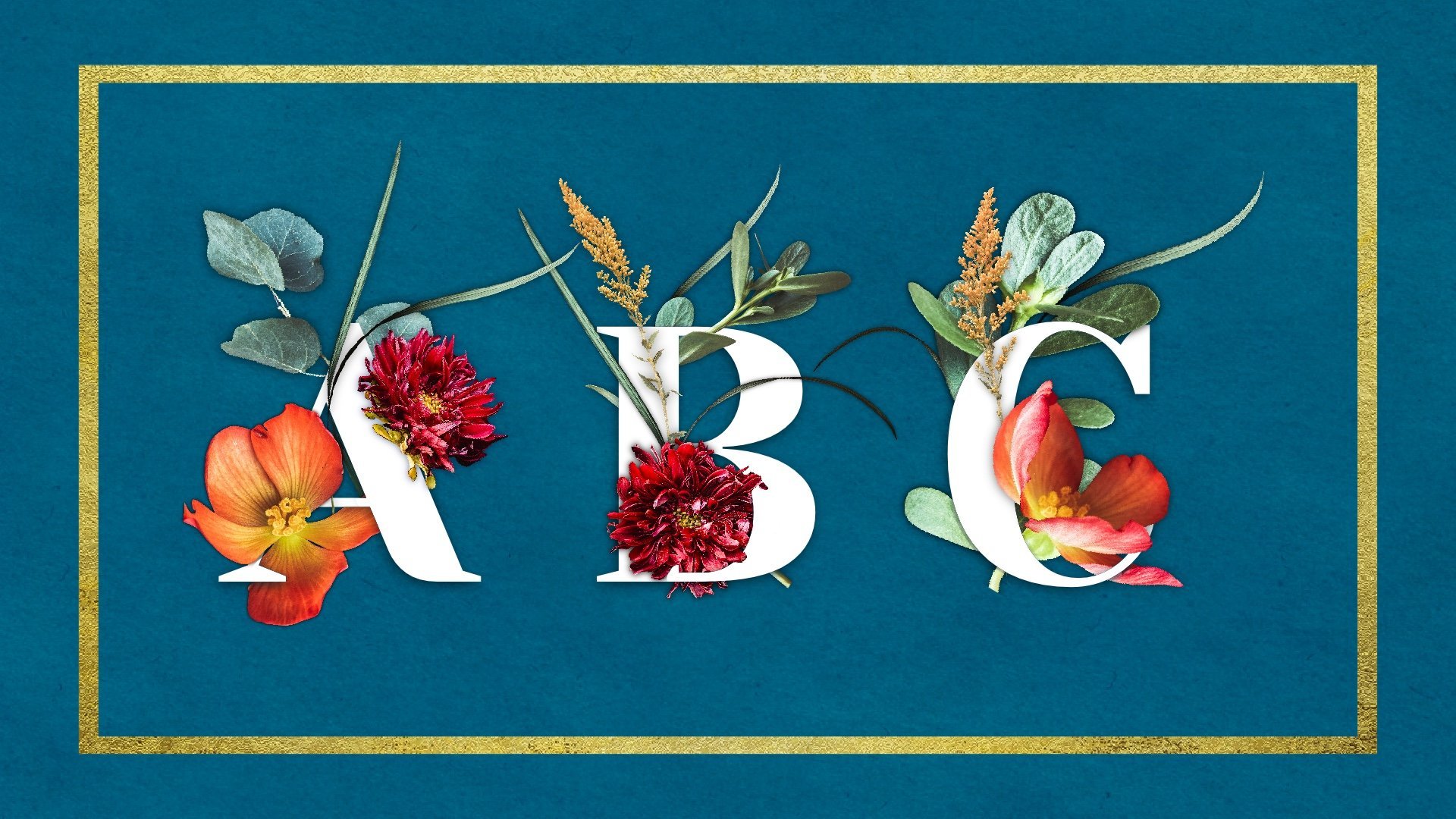
Masquage Procreate : créer une typographie époustouflante avec des fleurs entrelacées
Polices dans Procreate
Masques d'écrêtage dans Procreate
Masques de calques dans Procreate
Pratique plus de masque de couches
Entrelacer des fleurs avec une lettre
Floraux entrelacés avec un nombre
Bonus ! Astuces de masquage pour les réseaux sociaux
À propos de ce cours
Ce cours porte sur une seule chose : le masquage dans Procreate. À la fin de ce cours de 53 minutes, vous comprendrez les masques d'écrêtage et les masques de calques dans Procreate.
Pour le projet de cours, nous allons créer une belle typographie florale en utilisant du texte dans Procreate. Nous entrelacerons de magnifiques fleurs et feuilles numériques avec une seule lettre ou un seul numéro. Le projet est intentionnellement simple et vous pouvez donc vous focaliser sur les bases du masquage de calque.
Comme nous utilisons des fleurs et du texte numériques dans Procreate, des créatifs de tous niveaux pourront participer. Aucune compétence en dessin n'est nécessaire !
De cours, nous allons :
• Parcourir des polices gratuites dans Google Fonts
• Passer en revue brièvement Alpha Lock dans Procreate
• Explorer rapidement les masques d'écrêtage dans Procreate
• Entrelacer fleurs et feuilles avec une seule lettre en utilisant des masques de couches
• Entrelacer fleurs et feuilles avec un seul nombre en utilisant des masques de couches
1. Bande-annonce du cours: Bonjour, je suis Kelly Brand Burke. Je travaille en tant qu'artiste indépendant depuis 2013. J'adore créer de l'art numérique avec l'application Procreate. Et je vais vous raconter une petite histoire sur l'époque où j'ai commencé à créer de l'art numérique dans Procreate. C'était en 2015. Je n'arrêtais pas de voir ces magnifiques images entrelacées de mots, et je voulais vraiment apprendre à le faire. J'ai donc fait ce que je fais toujours. J'ai cherché mon intérieur sur Google, Google m'a dit que les masques à couches étaient la solution. J'ai trouvé des tutoriels YouTube sur le masquage dans Procreate géniaux, non ? Sauf que mon expérience n'a pas été géniale cette fois. J'adore apprendre grâce aux tutoriels YouTube. J'ai même créé des tutoriels Procreate sur YouTube. Mais pour ce sujet, enseignant passe à travers des masques à couches comme si c'était la chose la plus simple au monde. Je suis une artiste autodidacte, mais je n'arrivais pas à me concentrer sur les masques multicouches. Le découpage des masques était assez simple, mais les masques en couches, je n' arrivais pas à l'obtenir. Finalement, je l'ai découvert. Et puis, au bout d'un moment, j'ai oublié. Rincez et répétez l' ensemble du processus pendant des années. J'ai créé ce cours pour que vous puissiez comprendre le masquage dans Procreate. Ce cours se concentre sur une seule chose, le masquage dans Procreate. Pour le projet de classe, je vais vous expliquer comment s' entrelacent de magnifiques fleurs et feuilles à l'aide d'une seule lettre, puis d'un seul chiffre. À la fin de ce cours, vous comprendrez le masquage et comment entrelacer des images et des textes, puisque nous utilisons des fleurs numériques et des textes dans Procreate, les créatifs de tous niveaux seront capables pour participer. Aucune compétence en dessin n' est requise pour ce cours. J'utiliserai mon iPad, l'application Procreate de mon Apple Pencil, mais n'importe quel stylet compatible fera l'affaire. Mais attendez, il y a plus encore. Vous recevrez les meilleures fleurs et feuilles numériques. Je pourrais trouver une liste de polices gratuites suggérées et belles textures de fond prêtes à explorer le masquage dans Procreate. Allons-y. 2. Projet et ressources du cours: Le projet de classe consiste à entrelacer belles fleurs et feuilles avec une seule lettre, un seul chiffre ou les deux. Le projet de classe est volontairement simple afin que vous puissiez vous concentrer sur les bases du masquage des couches. Mais d'abord, nous allons parcourir les polices gratuites sur Google et choisir une police pour votre projet. Ensuite, nous explorerons la découpe de masques dans Procreate. C'est une leçon rapide. C'est à peu près cinq minutes. Nous allons passer le reste du cours sur les masques à couches. Je vais vous guider à travers chaque étape pendant que nous entremêlons des fleurs avec d'abord une lettre, puis un chiffre J'ai des atouts de classe pour vous aider, y compris une variété de textures de fond, une liste de polices gratuites suggérées et les meilleures fleurs numériques que j'ai trouvées chez Katherine d'Avalon Rose Designs. Elle nous fournit généreusement de magnifiques fleurs et feuilles. J'ai également créé un guide étape par étape sur les masques de couches. Il n'y a que trois étapes pour utiliser les masques de couches. L'astuce est que vous devez utiliser les trois étapes dans le bon ordre à chaque fois pour accéder à ces goodies, appuyez sur l' onglet projet et ressources de votre navigateur. J'ai hâte de voir ce que vous allez créer. Merci de partager votre projet sur Skillshare. Téléchargez votre projet en cliquant sur l'onglet Projet et ressources. Si vous avez des questions, je vous demande de cliquer sur l'onglet Discussions de Skillshare. Je répondrai à toutes les questions. Téléchargez donc les ressources de la classe, et je vous verrai dans la prochaine leçon. 3. Polices dans Procreate: Bon retour. Dans la dernière leçon, nous avons abordé notre projet de classe dans nos ressources pédagogiques. Dans cette leçon, nous allons parler de l'utilisation de polices dans Procreate. Procreate est fourni avec une variété de polices. Et je vais vous montrer une excellente ressource pour certaines polices gratuites, savoir les polices Google. Passons donc à notre navigateur Web et nous pouvons saisir des polices Google. Je vais en parler. Et vous pouvez voir qu'il y a beaucoup de polices différentes ici. Je ne sais pas combien, mais il semble y avoir une infinité de polices ici. Désolée, pas désolée pour le jeu de mots. Pour ce projet, nous allons utiliser des lettres majuscules individuelles. Je vais donc juste le taper ici pour que nous puissions voir à quoi cela ressemble. Et nous allons également utiliser certains chiffres. Voici donc nos a, b, c et 123, et nous avons beaucoup de polices. Ce que nous pouvons faire, c'est affiner cette recherche. Nous pouvons le faire en consultant différentes catégories, des empattements et Sarah pour l' écriture manuscrite, etc. Mais pour nos besoins, nous voulons juste une police assez épaisse parce que nous faisons l'entrelacement. Et si vous imbriquez quelque chose avec une police fine, ce ne sera pas aussi évident. Nous allons donc passer aux propriétés des polices. Nous allons taper sur l'épaisseur, la déplacer complètement vers la droite. Nous ne verrons que les polices les plus épaisses ici. Pour ce projet, je vais créer une police épaisse d' apparence plus classique. Ils ne le font donc pas vraiment pour moi. J'aime beaucoup cette police Erica One. Il a une touche rétro et je l'ai déjà téléchargé en appuyant sur télécharger la famille. Je l'aime beaucoup. Il n'y a tout simplement pas beaucoup d'espace pour la partie entrelacée ici. Je ne l'aime donc pas pour cette application, mais c'est une police cool. Et nous voulons voir plus de polices volumineuses. Donc, ce que nous allons faire, c'est revenir à cette épaisseur et ramener cette flèche un peu vers la gauche. Nous pouvons donc voir des polices plus volumineuses. Il y a une police ici appelée Railway. Ça m'a beaucoup plu. J'aime le monastère où l'un ou l'autre fonctionnerait. J'ai en fait une liste de quelques polices suggérées qui se trouvent dans la zone du projet de classe. Voici donc quelques suggestions de polices Google gratuites, puis il y a des polices par défaut pour créer qui dépendent de votre iOS. Donc, allons-y, vous en recevez un ici. Je vais le chercher. Et il n'apparaît pas parce qu' il est sur cette épaisseur. Voici, vous voyez V1, c'est une police vraiment cool. Je l'aime beaucoup. Mais certaines polices ont ce qu'ils appelleraient ici une famille plus large. Il y aurait donc des options, peut-être une option en forme de bloc ou une option en italique, mais celle-ci n' a qu'un seul type. Nous allons donc appuyer sur Télécharger la famille. Et nous allons dire oui, nous voulons le télécharger. C'est un fichier zip. Cela se trouve juste ici dans nos téléchargements. Et si nous l'appuyons, nous pouvons le rechercher dans nos téléchargements. Et ce sera un fichier zip. Et pour le décompresser, vous aurez besoin d'une application de décompression. J'utilise eyes zip Pro. Il me demandera si je veux décompresser les fichiers. Je dis oui, je tape à nouveau dessus et il me dira que le format n' est pas supporté et les yeux levés. Je veux donc l' ouvrir dans Procreate. Et juste comme ça, ce sera dans Procreate. Permettez-moi de prendre un blanc et je vais simplement vous en montrer un peu plus sur les polices de caractères dans Procreate. Je vais donc utiliser une clé à molette, ajouter du texte, et la police sur laquelle je suis en ce moment est future. Euh, c'est celle que j'ai recommandée pour cela et c'est une police Procreate par défaut. J'ai donc la police Futura. Je vais juste taper mon nom ici et je peux aller modifier le texte. Je veux appuyer dessus et tout sélectionner lorsque les lignes bleues qui l' entourent sont sélectionnées. À partir de là, je peux faire différentes choses. Je suis sur Futura. Je pense que c'est audacieux. Je peux faire un condensé, un extra gras, un gras et un italique moyen. Je vais juste m'en tenir à ce qui est audacieux. Tu peux mieux le voir. Je vais agrandir la taille en le faisant glisser parce que cette zone de texte est trop petite. Cela a fait ressortir le pourquoi. Je vais vous montrer comment résoudre ce problème. Si vous êtes dans les textes d'édition, vous pouvez saisir ces lignes bleues et simplement les étirer. Donc, encore une fois, si je clique sur Modifier les textes et que tout est sélectionné, nous pouvons faire autre chose avec. Nous pouvons tout faire en casquettes. On peut le centrer. Nous pouvons le justifier à gauche, nous pouvons le justifier à juste titre. Nous pouvons l' agrandir ou le réduire. Nous pouvons modifier la police à une taille spécifique en écrivant dans cette case. Il est actuellement de 93,2 points. Disons que je veux que ce soit 97 points pour une raison quelconque. Tu peux juste écrire ça dedans et ça changera. Il y a quelques options ici. Pour nos besoins. Je vais juste parler suivi et de la location, car ce sont les éléments les plus utiles. Suivi, si vous le déplacez dans une direction positive, cela fera s'étaler les lettres. Si vous le faites dans une direction négative, lettres seront condensées. Pour les besoins de ce cours, nous voulons probablement que les lettres soient un peu plus éloignées. Si nous écrivions plus d'une lettre, je vous recommande de commencer par une seule lettre. Mais si vous faites un mot, vous pourriez avoir besoin d'un peu d'espace pour que les choses puissent s'imbriquer. Nous allons maintenant regarder Letting, qui est l'espace entre les mots. Encore une fois, si nous le mettons dans une direction positive, cela augmente la taille entre les mots. Et si nous le mettons dans une direction négative, cela condense l'espace entre les mots. Je vais rarement dans une direction négative pour l'un ou l'autre d'entre eux, mais ils peuvent être utiles pour différentes applications. C'est la police dans Procreate que j'utilise dans le futur. Si je voulais l'éditer avec une autre police, je vais appuyer sur Sélectionner tout et revenir à AAA. J'ai un certain nombre de polices différentes ici. J'ai téléchargé certaines d'entre elles, comme la police CVA, et d'autres sont utilisées par défaut avec Procreate. Il y a donc un aperçu rapide des polices dans Procreate. La prochaine leçon, nous allons parler de la découpe des masques. Je te verrai dans la prochaine leçon. 4. Masques de clipage dans Procreate: Bon retour. Dans la dernière leçon, nous avons parlé des polices. Dans cette leçon, nous allons parler de la découpe de masques. Pour ce faire, je vais juste commencer par dessiner un cercle. Je vais utiliser la ligne mono, qui est le pinceau Procreate par défaut dans le kit de calligraphie. Voici donc le set de calligraphie, voici le pinceau monoline. C'est une bonne brosse polyvalente. Je vais faire un cercle blanc. En plus de ce bleu, j'ai une nouvelle couche. peux simplement dessiner un cercle approximatif et je peux appuyer sur Modifier la forme pour en faire un cercle parfait. Je peux prendre le blanc et en faire un cercle entièrement blanc. Pour créer un masque de découpage, vous devez ajouter une couche au-dessus du cercle blanc. Et puis vous appuyez sur le masque de découpe ici. Ensuite, vous verrez cette flèche indiquant que cette couche est découpée sur ce cercle. Cela signifie que tout ce que nous dessinons sur cette couche de masque de découpage ne s' appliquera qu'aux pixels de cette couche lorsque vous cliquez dessus. Je vais donc vous montrer ce que je veux dire. Je dessine partout et ne dessine que sur le cercle blanc. Si je défaisais le masque à découper, vous pourriez voir que j'ai dessiné partout. Mais si je clique sur Clipping Mask, il ne s'applique qu' à ce cercle. C'est donc utile car il s'agit d'une manière non destructive de modifier votre travail. Et cela signifie que vous pouvez toujours revenir en arrière et changer les choses. Vous pouvez activer et désactiver cette couche. Vous pouvez changer la couleur en la verrouillant en alpha. Tu peux faire plein de choses différentes. Vous pouvez appuyer sur cette flèche et la déplacer. Tu peux le réduire. Tu peux l'agrandir. Tu comprends. Vous pouvez faire toutes sortes de choses ici. Vous pouvez en fait avoir autant de masques à découper que vous le souhaitez. Vous pouvez le faire simplement en accédant à cette couche et en appuyant sur Nouvelle couche. Et chaque nouvelle couche que vous ajoutez entre les deux, la couche découpée et le cercle Procreate supposera que vous voulez un masque de découpage. Vous pouvez donc aussi y ajouter des pois jaunes. Nous avons donc maintenant notre cercle blanc ou nos pois jaunes. Vous pouvez déplacer les masques de manière les pois jaunes se trouvent au-dessus des lignes bleues. Vous pouvez modifier les couleurs. Encore une fois. J'ai beaucoup aimé cette orange. Je vais donc changer cela à nouveau. Et tout cela n'est pas destructif. Vous savez, sur Procreate, vous pouvez probablement annuler des choses avec deux doigts et les refaire avec trois doigts. Et vous pouvez le faire à tout moment. Mais avec cela, vous pouvez sortir du canevas, y revenir plus tard et vous pouvez toujours modifier ce que vous voulez. Vous pouvez vous débarrasser des lignes, vous pouvez vous débarrasser des pois. Je pense que tu comprends. Vous pouvez également ajouter une image sur le masque de découpage. Je vais récupérer un fichier récent ici. Et voici d'autres fleurs d'Avalon Rose, je ne vous recommande pas de faire tout cela, mais vous pouvez avoir toutes ces différentes couches. Il s'agit donc de découper des masques et, si vous les annulez, vous pouvez tout voir et les refaire. En appuyant sur le masque à clipser. Vous pouvez obtenir un effet similaire grâce à un verrou alpha, mais c'est une manière destructrice de modifier. Et je vais te montrer ce que je veux dire. Je vais donc supprimer ces gars. Nous avons notre cercle. Si nous utilisons un médaillon alpha, il fera quelque chose de similaire. Nous avons donc l'orange, nous avons les pois. Nous pouvons dessiner juste au-dessus de notre cercle blanc et avoir les points qui ne sont appliqués que là. Et c'est avec un Alpha Lock. Et quand tu portes ton médaillon, tu obtiens ce petit truc en damier en dessous. Mais le truc, c'est que maintenant je veux des cercles jaunes. Je ne peux pas le faire aussi facilement. Je veux dire, il pourrait essayer de le laisser tomber en couleur. Je pourrais ramasser ce blanc et le rendre à nouveau blanc en remplissant la couche puis faisant des points jaunes dessus. Mais c'est destructeur. Si je quitte le canevas et que je le ramène à nouveau, je ne peux pas toucher deux doigts pour annuler. C'est juste comme ça. Alors qu'auparavant, nous pouvions facilement supprimer ou modifier les couleurs des masques de découpe. Le verrouillage alpha est donc utile si vous êtes limité aux couches et que vous savez exactement quelles couleurs vous voulez Je ne l'utilise presque jamais simplement parce que le masque de découpage est un moyen non destructif et que je préfère utiliser ça. est ainsi que vous utiliseriez Alpha Lock. Encore une fois. Je pourrais faire en sorte que cette couleur, ce cercle soit entièrement jaune. Et elle est verrouillée par alpha. Et je pourrais choisir une autre couleur, adorant cette orange aujourd'hui. Et il est bloqué par alpha et je peux juste dessiner plus de points oranges dessus. Ou je pourrais ajouter de la texture ou ce que je voulais, mais c'est destructeur. C'était donc un aperçu des masques de découpage et du verrouillage alpha dans Procreate. Dans la leçon suivante, nous allons parler des masques de couches, qui constituent une autre méthode d'édition non destructive. Je te verrai dans la prochaine leçon. 5. Masques de couche dans Procreate: Bon retour. Dans la dernière leçon, nous avons parlé Alpha Lock et du découpage des masques. Dans cette leçon, nous allons parler des masques de couches. Ce que je vais faire ici, c'est ajouter du texte à titre d'exemple. Je vais juste écrire la lettre K. Je vais la rendre vraiment grande. Je vais changer la police en Admiral Fat Face. Et je veux vraiment que mon k soit blanc. Je vais donc appuyer sur cette couche, appuyer sur Modifier le texte, puis prendre un blanc à la place. Voilà notre lettre K. Ce que je vais faire ici c'est la rastériser juste pour qu'elle devienne les pixels de la page. Ils ont déjà écrit les étapes d'un masque de couche. Je vais donc les avoir en haut de la page ici tout le temps rappeler quelles sont les étapes spécifiques à suivre pour un masque de couches, beaucoup de choses avec Procreate, vous pouvez les faire différemment et cela peut être un peu des masques de couche indulgents. Devez-vous aller exactement dans le bon ordre pour obtenir l'effet que vous souhaitez ? Et je vais te montrer ce que je veux dire. Nous avons donc notre lettre K et nous allons ajouter autre chose en plus, je vais trouver de la farine ou des feuilles, et je vais les apporter ici. Je vais mettre les feuilles comme ça. Et donc en ce moment, les feuilles sont devant le k et nous voulons faire un look entrelacé. Nous allons utiliser un masque à couches. Pour créer un masque de couches, nous allons suivre ces étapes ici. Nous allons appuyer sur la couche supérieure et appuyer sur Masque. Et puis on obtient cette couche blanche au-dessus. Ensuite, nous passons au k, que nous voulons interagir avec les feuilles, et nous allons appuyer sur Sélectionner. Ensuite, nous allons revenir à notre masque à couches. Et comme notre masque à couches est entièrement blanc, vous pouvez voir que les feuilles sont au-dessus du k et c'est tout. Si nous voulions le rendre différent, nous prendrions un noir pur, qui, si vous regardez la partie valeur, indique un tas de zéros. Je pense que c'est six zéros. Et un blanc pur correspond à six F. Je vais donc revenir à mon noir, j'ai ma monoline et je vais retourner à mon masque superposé et je vais dessiner dessus. Quand j'ai cliqué sur Sélectionner, nous avons obtenu toutes ces lignes diagonales, que j'espère que vous pourrez voir si je zoome. Les lignes diagonales sont partout où le K et les feuilles ne se trouvent pas puisque c'est avec cela que nous travaillons. Supposons que je veuille faire croire cette feuille se trouve derrière la lettre K. Je suis sur le masque à couches et je dessine simplement en noir et cela donne l' illusion que la feuille se trouve sous le K. Et disons que nous voulions également le faire avec cela. Toute la tige. On continue juste à dessiner avec du noir ici. Disons que nous voulions ramener l'une des feuilles. Nous avons changé d'avis. Nous pouvons à nouveau choisir le blanc. Assurez-vous que nous sommes toujours sur le masque de couches et ramenez-le simplement en dessinant ici. Nous pouvons en ramener une partie seulement ou la totalité. Il s'agit donc d'un masque en couches. Je vais être un peu répétitif dans cette leçon, car il m'a fallu un certain temps pour comprendre les masques en couches. Je vais donc continuer à examiner de différentes manières dans cette leçon, je vais revenir à ce masque superposé. Disons que je n'ai pas appuyé sur Select, que je suis sur le masque de couches, que j'ai mon noir. Et ce qu'il fait ici, c'est qu'il cache tout parce que je n'ai pas sélectionné le k. Donc, c'est une erreur courante que k n'est pas sélectionné. Je peux le défaire. Et je suis retourné à la sélection. Nous allons donc suivre à nouveau ces étapes exactes. Nous appuyons sur le calque et appuyons sur Masque, sur le K, sur Sélectionner, sur Saisir un noir pur, que j'ai juste ici. Son code hexadécimal est composé de zéros, donc c'est bon. Et je reviens à mon Layer Mask. Et maintenant, je vais juste faire croire que certaines de ces feuilles sont derrière cette partie du K. Au lieu de cela. Voilà, nous avons un look entrelacé qui est à l'opposé de ce qu'il était avant. Permettez-moi de soulever une autre question afin que nous puissions voir de nouveau comment cela fonctionne. Je vais chercher une autre sorte de feuilles ou de fleurs ou quoi que ce soit d'autre. Et je vais arranger ça devant le k scan. Nous allons suivre ces étapes ici. Nous allons appuyer sur cette couche et appuyer sur Masque, appuyer sur ce k et appuyer sur Sélectionner. Nous obtenons les lignes diagonales qui sont partout sauf pour la feuille et le k. Nous revenons à la couche de masque. Nous avons une ligne noire et une ligne monochrome. Et nous commençons à dessiner en noir où nous voulons que les feuilles se trouvent derrière la lettre. Alors on y va. Faisons en sorte que ça ressemble à ce que c'est en dessous de mon dessin en noir. Je n'aime pas ça. Je pourrais donc soit taper deux doigts pour annuler soit parce que c'est une méthode non destructive, je peux simplement récupérer mon blanc pur et le colorer à nouveau. Reprenons plutôt notre noir. Si nous appuyons simplement sur cette couleur, cela nous amène à notre dernière couleur où les cylindres étaient monolignes. Supposons que vous souhaitiez que cela passe derrière, appuyez sur cette flèche et annulez la sélection. Et voici notre masque. Donc quand on a dessiné le noir dessus, ça a donné l' impression que les feuilles se trouvaient derrière la lettre K. Je vais le faire encore une fois pour que tu puisses le trouver. Si c'est le cas, vous pouvez passer à la leçon suivante. Mais comme je l'ai dit, c'est que j'ai eu du mal à comprendre ça quand je l'ai appris. Je vais donc y revenir une fois de plus. Je te verrai dans la prochaine leçon. 6. Pratique de masque de couche: Je vais faire un numéro cette fois. Je vais le faire, je vais changer les polices. Faisons Aperol Fat Face. Nous avons donc ici un huit. Je vais le modifier pour qu'il soit blanc. Et je vais juste le pixelliser parce que nous n'avons plus besoin de le modifier. Nous ajouterons à nouveau quelques fleurs. Je vais insérer ces fleurs roses. Et cela nous donnera une bonne occasion de nous imbriquer. Je vais déplacer ces mots vers le bas. On peut les voir, d'accord ? Nous allons donc suivre ces étapes. Nous allons appuyer sur cette couche et appuyer sur le masque. Lorsque nous faisons cela, nous obtenons un masque à couche blanche au-dessus des fleurs. Ensuite, nous passons à la couche avec laquelle nous voulons que les fleurs interagissent, qui est la huit. Et nous avons appuyé sur Select. Et là, nous obtenons les lignes diagonales sur tout sauf les fleurs roses et les huit. Nous revenons à notre masque multicouche et nous avons un noir pur. Maintenant, nous avons une ligne mono, et commençons simplement à jouer sur le masque de couches. Donc, si je dessine un noir ici, nous ferons croire que cette partie se trouve derrière les huit ici. Cela donnera l'impression qu' une autre pièce est derrière. Je pourrais le laisser tomber, mais ensuite on aura des problèmes avec celui-ci. Donc je ne veux pas faire ça. Donc je vais juste prendre un blanc et le ramener. Ou je peux accéder à mon masque de couches et appuyer sur Effacer. Donc, toutes les fleurs sont de retour. Laisse-moi retourner les fleurs, que ce soit différent. Nous avons donc notre masque de couche , puis nous passons au huit et appuyons sur Sélectionner. Nous revenons à la couche de masque. Nous appuyons sur le blanc pour le transformer en un noir pur. Je mets un masque à couches avec ma monoline. Disons que je veux faire croire que cette partie est en train de s'effondrer. Laisse-moi voir si ça a vraiment marché. Je pense que je vais aussi le faire ici. Laisse-moi continuer et voir ce qui se passe. Il y a quelques expérimentations à ce sujet parce que vous ne savez pas exactement à quoi vous voulez qu'il ressemble. Vous pouvez donc simplement jouer avec cette méthode de travail non destructive. Je vais appuyer sur cette flèche pour désélectionner des éléments. Maintenant, nous en avons une partie derrière et une partie devant. Et je vais juste essayer une dernière chose. Je vais effacer ce masque et suivre ces étapes une fois de plus. Nous avons donc un masque de couche, nous cliquons sur Sélectionner. Nous avons une ligne mono. Et je vais juste y mettre autre chose. Je vais dire je ne dis pas que je dessine sur le huit et le masque de couches. Il est très facile de faire ces erreurs. C'est assez facile de le réparer. Je vais faire passer ça en dessous. Sauf que je vais faire passer cette partie en dessous, mais pas trop haut pour un effet de chevauchement. Il est difficile de voir où cela commence à se terminer. Donc je vais juste laisser les choses comme ça. Je vais appuyer sur cette flèche et ça a l'air vraiment cool. J'aime bien ça. Là, nos huit entrelacés travailleront avec des masques en couches pendant le reste de la classe. Vous aurez donc de nombreuses occasions de voir d'autres masques à couches en action au fur et à mesure. Encore une fois, je vais également vous donner un document contenant les étapes à suivre pour les masques à couches , puis quelques erreurs courantes que vous pourriez commettre. La leçon suivante, nous allons choisir une lettre, et nous allons créer plusieurs fleurs et feuilles entrelacées avec une lettre en forme de fan. Je te verrai dans la prochaine leçon. 7. Florales intertwine avec une lettre: Bon retour. Dans la dernière leçon, nous avons pratiqué le masquage dans Procreate. Ensuite, nous allons transformer cette pratique en une application plus pratique. Nous allons entrelacer les fleurs et les feuilles avec une seule lettre. Allons-y. J'ai déjà créé un canevas dix par dix. C'est ce que je vais utiliser. Vous pouvez utiliser la taille que vous souhaitez. Mais pour créer un canevas dix par dix, vous devez appuyer sur Plus un nouveau canevas. Et procreate utilisera par défaut les pixels, mais nous voulons des pouces et nous pouvons simplement faire 10,10. Et si nous voulions donner un nom à cette toile, nous pourrions la nommer dix sur 10 pouces et 300 DPI, ce qui représente une excellente qualité d'impression. Ensuite, nous cliquions sur Créer. Et puis nous aurions un nouveau Canvas dix par dix. Mais comme je l'ai déjà préparé, je vais simplement le supprimer en balayant vers la gauche et en appuyant sur Supprimer. Voici donc ma toile dix par dix que j'ai déjà préparée. Je vais aller à la clé, ajouter et ajouter du texte, modifier le texte en appuyant sur Modifier le texte. Et je vais juste supprimer les textes des mots et les mettre dans la lettre S. Vous pouvez utiliser la police de votre choix. Vous voyez, même l' une d'elles est une police Google gratuite, et il existe d'autres polices suggérées. Dans une leçon précédente, je suis sur mon S, je vais appuyer sur Modifier le texte, appuyer sur ce S et appuyer sur Tout sélectionner. Et pour modifier ce S, je vais appuyer sur ce AAA pour afficher ce menu. Et comme je fais une série de lettres, je veux que les lettres aient toutes la même taille. Donc, pour mon but, je vais gagner 75 points. Et je peux juste écrire dans cette petite boîte. Et là, nous avons un S. de 475 points et la plupart du temps, si je fais un projet comme celui-ci, je renommerai cette couche, vous CVA pour 75. Et cela m'aide simplement à rester organisée. lorsque je le revisiterai plus tard, je saurai exactement de quelle police il s'agissait, pas exactement de quelle taille. Nous avons donc notre S et ce que je vais faire, c'est le centrer. Je vais appuyer sur cette flèche et j'ai sélectionné et accroché un uniforme, donc je peux simplement le déplacer. C'est donc un bon début. Et ce que je vais faire, c'est ramener les instructions que nous avons utilisées tout à l'heure. Je vais les ajouter à une nouvelle couche au-dessus que nous pouvons activer et désactiver. Maintenant que nous avons nos rappels en haut de la page, commençons à ajouter des fleurs. J'ai déjà importé des fleurs pour cela. Ils proviennent d'un bundle d' Avalon Rose appelé Spellbound. Catherine de Spellbound nous a offert des fleurs à utiliser, et elles se trouvent dans la zone des projets et des ressources de la classe. J'ai mes fleurs ici et je vais juste les dupliquer et commencer à les mettre en valeur ici. J'aime dupliquer les choses. Alors j'ai l'autre encore disponible et édité en bas. Maintenant qu'ils sont là, je vais les éteindre. Je commence donc généralement par une feuille ou un gros élément que je vais vouloir entrelacer. Si vous pensez à un livre, les feuilles sont généralement à l'arrière et les fleurs à l' avant et au centre. Nous avons donc cette jolie tige et je vais la réduire un peu. J'ai appuyé sur la flèche de sélection et c'est en uniforme. Et ce que je recherche, c'est qu' il y a des éléments qui peuvent entrelacer et interagir avec le S. Et pour nous y aider, nous pouvons utiliser Warp et Advanced Mesh. Ensuite, nous pouvons tirer sur n'importe lequel de ces nœuds bleus. Il y a donc de nombreuses possibilités de faire passer les feuilles sous ou au-dessus. Et en général, entremêlez-vous. J'ai aimé son apparence, donc je vais appuyer sur cette flèche et appuyer sur OK. Je pense que je pourrais faire ressortir cette feuille un tout petit peu. Je suis toujours en distorsion. Je veux revenir à l' uniforme parce que j'ai aimé sa taille actuelle. Je sais que je ne veux pas ce long stock en bas, donc je vais juste prendre ma monoline comme gomme. Efface juste les parties que je ne veux pas. Je vais commencer en entrelacant cette feuille et en voyant où nous en sommes. Encore une fois, il s'agit d'une méthode d' édition non destructive qui nous permet d' annuler facilement ce que nous voulions faire. Je suis donc ces instructions ici. Je tape sur la couche de feuilles et je tape sur le masque. Et je veux qu'il interagisse avec ce S. Donc je vais appuyer sur Select. Et je vais trouver ces lignes diagonales ici. Et je veux naviguer vers un noir pur. Le code hexadécimal est composé de six zéros, et j'ai mon pinceau monoline. Vous pouvez utiliser un certain nombre de pinceaux différents pour cela, mais la gamme mono est une bonne brosse polyvalente. Ce que je dois faire maintenant, c'est revenir à la couche blanche avec ma ligne monochrome noire. Ensuite, je peux commencer à interagir avec les feuilles et la lettre et voir ce que j'aime ici. Ce faisant, vous effacez uniquement les endroits où les feuilles et le S interagissent ici. Nulle part ailleurs Si cela ne nous plaisait pas, nous pourrions toujours revenir à un blanc pur et simplement annuler tout ce que nous faisions. Nous avons toujours la sélection en cours. Nous revenons au masque de couches. Et si nous voulions dire ramenez cette feuille toute seule ou celle-ci, alors nous pouvons la ramener facilement. Et c'est ce que je veux dire par. Non destructif. Nous devons donc désélectionner cette option. Nous revenons donc à cette flèche et la désélectionnons. Et je vais ajouter une fleur ici. Donc je vais aller voir la sélection, je porte l'uniforme, je vais le réduire un peu et je vais chercher occasions de m' entrelacer ici, ce que je pourrais avoir envie de faire, c' est de le mettre en dessous ici. Il est facile d'oublier que nous voulons que ce soit toujours un S illisible, n'est-ce pas ? Nous voulons donc garder cela à l'esprit tout le temps. Ici, j'ai ajouté quelques jolies petites branches florales. Même s'il ne s'agissait pas de deux branches différentes, nous pouvons leur donner un aspect très différent. Par exemple, laissez-moi en désactiver un et nous ne travaillerons qu'avec celui-ci. Je vais donc appuyer sur cette flèche et je vais la réduire un peu. Et nous allons nous entraîner à le mettre ici. Supposons que nous voulions le réutiliser et que nous voulions lui donner un aspect différent. Je peux le déplacer ici appuyer sur cette flèche et basculer horizontalement, ça a automatiquement un aspect différent. Nous pouvons le faire paraître plus petit, puis nous pouvons aussi le déformer en lui donnant un aspect incurvé. Vous devez juste être conscient que vous ne le déformez pas. Donc ça a l'air vraiment bizarre. Il est donc très efficace pour conserver l' intégrité de l'objet. Mais il vaut mieux que vous ne le fassiez qu'un petit peu. Je vais appuyer avec deux doigts pour annuler cela, revenir à la distorsion et ensuite la courber subtilement. Et puis nous en avons un autre qui est différent. Je l'allume et je vais passer à cette flèche, réduire encore un peu. Donc, ce que nous allons faire, c'est avoir tout cela sous cette fleur. Donc je vais en parler et ça a l'air très fréquenté maintenant, je pense que je pourrais placer certaines de ces branches sous le S qui pourraient être belles. Je vais commencer par placer celui-ci juste ici sous le S. Et je vais vouloir effacer ces tiges aussi en bas. Mais pas encore, pas avant d'avoir fini. Celui-ci a l'air bien tel qu'il est. Je pense que ce petit ranch, je vais le rétrécir un peu. Si je prends ce nodule vert, je peux le faire pivoter de 15 degrés à chaque fois. Mais si je veux une rotation plus subtile, je peux prendre ce nodule jaune et mettre où je veux. Je trouve que ça a l'air plutôt bien. En fait, cela semble un peu occupé en ce moment, mais je ne pense pas que ce sera le cas une fois nous aurons fait un peu d'entrelacement. Alors faisons-le. Je pourrais placer cette partie sous la cote S. Laissez-moi vous montrer ce que je veux dire. Donc je n'ai pas pris la bonne farine. Je suis sur cette fleur. Je vais suivre ces étapes ici. Je vais appuyer sur cette couche et appuyer sur Masque. Je vais passer aux tâches avec lesquelles il interagit, et je vais appuyer sur Sélectionner. Je comprends mes lignes diagonales. J'ai un noir pur, qui est un code hexadécimal composé de zéros. J'ai ma ligne mono et je vais les ranger. Qu'est-ce que je fais mal ? J'ai du blanc, c'est mon problème. Le truc avec le masquage, c'est que beaucoup de choses peuvent mal tourner. Donc, si je suis sur mon calque et que je dessine avec du blanc, j'ajoute simplement du blanc au blanc, ce qui revient exactement à la même chose. Au lieu de cela, je vais prendre mon noir et ma monoline et m'assurer de porter mon masque superposé. Et je vais juste mettre ça en dessous. Je pense que je vais avoir cette partie en haut parce que les feuilles sont en bas. Je pense que ça a l'air bien en ce moment. Donc je vais juste le désélectionner en appuyant sur la flèche, ces tiges m'embêtent vraiment, donc je vais juste les effacer. Je ne sais pas sur lequel je suis, mais vous pouvez simplement faire des essais et des erreurs ici. Parfois, j'aime avoir une petite tige qui sort et parfois non, c'est juste une question de préférence. Je vais regrouper ces couches afin que nous puissions les déplacer un peu vers le bas afin qu'elles n' interagissent pas avec nos instructions là-haut. Je vais donc balayer vers la droite et appuyer sur Grouper. Et maintenant, nous avons notre S et toutes nos fleurs et je vais juste le réduire un peu. Passons maintenant à cette jolie fleur. Nous allons à nouveau suivre les étapes. Là-haut. Nous allons appuyer sur la couche de fleurs et appuyer sur Masque pour qu'elle interagisse avec le S. Nous allons donc appuyer sur Sélectionner. Nous allons revenir au masque à couches avec notre ligne noire et notre ligne monochrome. Et je vais essayer de simplement mettre une partie de cette feuille en dessous. Et je vais laisser cette petite feuille là-haut. Ou je pourrais, je veux vraiment laisser ça ici. Cette partie est visuellement cachée en dessous. J'appuie sur la flèche pour désélectionner, je vais désactiver notre itinéraire ici. Je pense que ça a l'air bien. Nous avons des entrelacements. C'est lisible. Je pense que c'est clairement un S Et je pense que c'est vraiment joli. Si je voulais dire que j'irais Share JPEG, puis je l'enregistrerais sur ma pellicule en appuyant sur Enregistrer l'image. Maintenant que nous avons entrelacé des fleurs et des feuilles avec une seule lettre, nous allons passer à la leçon suivante, qui consiste à entrelacer des fleurs et des feuilles avec un seul chiffre. Je te verrai dans la prochaine leçon. 8. Florales intertwine avec un nombre: Bon retour. Dans la dernière leçon, nous saisissons des fleurs et des feuilles entrelacées avec une seule lettre. Dans cette leçon, nous allons poursuivre notre pratique du masquage en entrelacant des fleurs et des feuilles avec un chiffre. Alors allons-y. Je vais utiliser la même toile que celle que j'ai utilisée auparavant. J'ai renommé ce groupe S, et je vais le placer sous ma texture bleu sarcelle ici. Pour celui-ci, je vais faire un numéro et je vais en faire six. Je vais donc récupérer mon blanc à nouveau. Je vais aller chez Wrench. Je vais ajouter du texte. Je vais supprimer les textes et en taper six. Et maintenant, je dois le sélectionner à nouveau en sélectionnant tout. Je vais appuyer dessus et revenir au clavier. Ensuite, je vais écrire pour 75, encore une fois pour la police. Et cela n'a pas changé et c'est parce que je ne l' ai pas sélectionné. Je pensais l'avoir fait, mais je ne l'ai pas fait. Sélectionnez donc tous les AAA. Et puis nous en avons 475 ici. Si je l'écris là, on y va. Maintenant, nous avons un chiffre qui a exactement la même taille que notre lettre S. Je vais ramener nos directions ici, et je vais centrer nos six. J'ai d'autres fleurs ici que j'ai déjà importées. Pour importer une fleur, il suffit d'utiliser une clé à molette, d'insérer un fichier. Et vous les auriez déjà enregistrés dans vos fichiers ou votre pellicule photo, puis vous n'auriez qu'à appuyer sur Insérer. Et nous ne pouvons pas le voir parce qu' il se trouve sous cette sarcelle, mais là, il est au-dessus. Donc je vais juste mettre ça en dessous jusqu'à ce que nous décidions de ce que nous allons faire. Je vais commencer par dupliquer ces feuilles parce qu'elles sont belles et sinueuses et je pense qu'elles interagiraient bien avec les six. Je vais utiliser notre astuce de déformation pour nous donner plus de possibilités d'entrelacement. Donc je suis sur les feuilles, je vais voir cette sélection et elle est en uniforme, ce qui est un bon endroit par défaut pour que ça reste. Mais je vais passer à Warp et Advanced Mesh. Et je vais juste commencer à faire bouger les choses. Veiller à ne pas trop en déformer l'apparence. C'est juste une sorte de courbe autour des six. Je pense que ça a l'air bien. Je vais prendre la gomme, la gomme monoline, et me débarrasser d'une partie de la tige ici. Je voudrais peut-être que ça ressorte un peu. Je n'en suis pas sûr. Je vais donc laisser ça là. Maintenant que c'est fait, retrouvons ces petites fleurs jaunes. J'aurais aimé connaître le nom de toutes ces fleurs, mais super. Et je vais juste les regrouper pour m'organiser. Alors, glissez vers le groupe de droite, et je vais renommer ce groupe six. Nous avons donc étiqueté notre groupe. Je vais amener nos deux actions au sommet. Je pense que ce que je vais vouloir ici c'est que certaines de ces fleurs jaunes soient totalement derrière les six et d'autres au sommet. Nous n'avons donc pas nécessairement besoin d'avoir des éléments entrelacés pour lui donner cet aspect entrelacé simplement en le repliant. Disons ce gars en dessous. Nous avons donc notre deuxième fleur jaune. Je vais appuyer sur cette flèche et je vais commencer par l'uniforme en le réduisant. Je vais juste prendre un de ces nodules bleus et le réduire un peu. Ensuite, je vais revenir à Warp Advanced Mesh et jouer avec la façon dont il pourrait interagir avec cet ensemble de feuilles. Et puis nous avons ces feuilles qui sont derrière ici et qui sont un peu cachées. Je vais donc prendre cette flèche. Et d'abord, je vais porter l'uniforme. Je vais juste les cacher derrière ces feuilles. Et en plus de cela, je vais apporter une jolie fleur d'oranger. Et ce sera tout en haut. Et je vais le réduire. Et je vais vous parler de l'un de ces petits pétales en dessous. J'aime bien cette fleur parce que , par exemple , je pourrais mettre cette partie en dessous gardant les autres dans les laboratoires. Je pense que je devrais peut-être le réduire un peu , car n'oubliez pas que l'une des parties importantes est de s' assurer que ce chiffre est toujours lisible. Ce n'est pas totalement lisible pour le moment, mais nous n'avons pas encore commencé notre entrelacement. Je vais commencer par nos feuilles ici. Je vais suivre nos étapes ici. Je vais donc taper sur les feuilles. Je vais appuyer sur Mask. Je vais appuyer sur ce six et appuyer sur Sélectionner. Nous obtenons nos lignes diagonales. Et au lieu du blanc, je veux du noir. Et je veux ma gamme de modèles. C'est juste là. Et je reviens à mon Layer Mask. Et je vais commencer à cacher les choses. Je ne sais pas exactement quel itinéraire et je voulais emprunter, mais commençons par en mettre un peu en dessous car nous allons avoir plus de fleurs jaunes au-dessus d'ici. Je pense que c'est une bonne idée pour commencer. Je vais donc appuyer sur ma flèche et la désélectionner. Je vais m'appuyer sur ce groupe et le réduire un peu. Il est donc distinct de ce texte là-haut. Ça a l'air plutôt bien. Je vais ramener cette autre fleur jaune et cette fleur orange et voir à quoi ça ressemble. Je pense que ce que je veux faire, c'est le déformer un peu plus. Donc je suis sur la flèche, je suis sur le quai. Je suis un maillage avancé et je vais juste me courber un peu plus. Je trouve que ça a l'air sympa. J'ai mes tiges ici, que j'effacerai plus tard, mais je ne vais pas le faire tout de suite. Maintenant, je vais aller voir cette fleur d'oranger et je vais appuyer sur Mask. En suivant les étapes ci-dessus, revenez à mes six, appuyez sur Sélectionner. Je prends de la monoline noire, et je reviens à ma couche orange et je vais essayer voir à quoi ça ressemble cette feuille en dessous. Et nous verrons si cela a un sens visuel. Je ne suis pas sûr que ce soit le cas, mais laissez-moi le désélectionner. Non, ça ne l'est pas. Donc, pas de soucis car c'est non destructif. Je vais nettoyer mon masque et je vais revenir à tout blanc. Laisse-moi essayer, en retournant cette fleur. Donc je vais retourner à l'uniforme. Je vais retourner cette fleur à l' horizontale et faire tourner cette fleur et c' est peut-être ce dont nous avons besoin. Je pense que cela pourrait nous donner une meilleure occasion de nous entrelacer. Et ce que je vais faire, c'est d'abord éteindre cette couche et effacer ces tiges parce qu'elles m'embêtent. J'ai ramené ma fleur d'oranger inclinons-la un peu pour voir à quoi elle ressemblerait avec cette pédale cachée sous les six. Je vais revenir à Warp et Advanced Mesh et juste retirer cette feuille un peu. Il y a donc un peu plus de choses qui ressemblent à de l'action entrelacée, vous pourrez donc en voir plus derrière les six. Alors suivons nos étapes. Nous avons un masque à couches. Nous allons passer à ces six, avec lesquels nous interagissons et nous allons appuyer sur Select. Et nous n'allons pas utiliser notre ligne monochrome noire pour voir si nous pouvons replier visuellement ce pétale. De toute évidence, je ne suis pas botaniste ici, mais j'adore vraiment les fleurs. Vous n'avez pas besoin d' être très précis à ce sujet jusqu'à ce que nous commencions à interagir avec un autre pétale que nous voudrions peut-être laisser par-dessus. C'est donc là que je suis un peu plus précis. Et je trouve que ça a l'air plutôt bien. Je vais donc appuyer sur Désélectionner. Je vais le ramener à l'uniforme parce que c'est exactement comme ça que j'ai l'habitude de le voir. Tu sais, je trouve que ça a l'air bien. Ce que je n'aime pas ici, c'est que la tige continue de ressortir. Faisons donc plus de masquage avec cette couche. C'est ça, ces feuilles. J'ai donc déjà un masque de couches, puis je passe à mes six et j'appuie sur Sélectionner. Et je vais juste rentrer visuellement cette tige en dessous. Je vais effacer le reste de cette tige parce que ce n'est pas le cas, oups, j'y suis. Maintenant, je dessine en noir plutôt que effacer sur cette tige. OK, donc ça a l'air terminé. Oh, je crois que j'aime ça. Je devrais peut-être revenir à cette fleur d'oranger, la sélectionner et retourner sur Warp. Et arrache juste un peu plus les feuilles. Il y a donc juste un peu plus d'entrelacement. Désactivons donc notre itinéraire ici et voyons à quoi cela ressemble. Tu sais ce que je suis quand je travaillais, j'ai foiré quelque chose ici. Effacons donc ce masque de couche et revenons à Select. Nous avons notre monoline noire. Et encore une fois, je vais juste le remettre en dessous. Je vais réduire la taille de ma monoline. Une fois que je me rapprocherai de cette feuille. Je trouve que ça a l'air sympa. Pour rappel, j'adorerais voir ce que vous créez. N'oubliez donc pas de partager vos projets. Vous êtes une lettre ou un chiffre, ou si vous étiez très ambitieux, un mot dans la zone de projet de classe. Et j'adore les voir et je commente tous ceux que j'aime partager. Les étudiants ont travaillé sur les réseaux sociaux, ainsi que sur Instagram. Donc, si tu veux que je t' emmène sur Instagram, ajoute ton pseudo Instagram, et je le ferai. J'ai aussi une leçon bonus très rapide pour vous. C'est une façon d' utiliser le masquage pour mettre en valeur votre travail sur les réseaux sociaux. Je te verrai dans la prochaine leçon. 9. Bonus ! Tricks de masquage sur les réseaux sociaux: Bon retour. Vous avez probablement vu ces astuces utilisées par d'autres artistes sur les réseaux sociaux et vous vous êtes demandé comment procéder. Et je vais vous montrer qu'ils sont très rapides et faciles et qu'ils peuvent être utilisés pour une variété d'œuvres d'art, pas seulement pour une œuvre entrelacée. Alors allons-y. Ce que je vais faire, c'est utiliser ces six points comme exemple. Et ce que je vais faire d' abord, c'est dupliquer en balayant vers gauche sur le canevas et en appuyant sur Dupliquer. Et j'ai besoin d'une œuvre d'art aplatie, ce qui signifie que je n'utilise pas toutes ces différentes couches. Et si j'ai fait une copie, c'est parce que je veux toujours conserver la pièce originale avec les couches au cas où je voudrais revenir en arrière et les modifier plus tard. Mais pour nos besoins, nous allons simplement supprimer ce dont nous n'avons pas besoin ici. Nous n'avons pas besoin de ces instructions. Nous n'avons pas besoin de ce six en bas. Et nous n'avons pas besoin de ces fleurs supplémentaires ici. Et je vais juste appuyer sur ce groupe et appuyer sur Aplatir. Et cela a rasé tout le groupe. Et ce que je peux faire pour l'aplatir davantage, c' est de les pincer ensemble. Maintenant, notre travail se fait sur une seule couche, ce dont nous avons besoin pour cette astuce. C'est une astuce de masquage. Je vais donc appliquer un masque sur cette couche. Et voici notre masque blanc. Comme le masque est blanc, il révèle tout ce qui se trouve en dessous. Mais si nous prenions six zéros d'un noir pur pour un code hexadécimal et que nous cliquions sur Fill Layer, alors nous avons cet écran vide ici. Mais comme nous le savons, le blanc révèle. Si on prend un blanc pur ici et qu'on peut prendre une monoline, agrandissez-la. Ce que nous pouvons faire, c'est ramener notre œuvre comme par magie de deux manières différentes. La première astuce est la plus simple, et nous allons prendre notre blanc pur, faire glisser le blanc vers le milieu de l'écran. On peut le garder ici et ensuite il remplira la couche. Alors, il y apparaît automatiquement. C'est donc une façon amusante de révéler votre travail. Et une autre façon de le faire serait de remplir à ce masque à couches nouveau ce masque à couches de noir pour dissimuler le tout. Et c'est celle que vous verrez peut-être le plus souvent. Vous saisiriez à nouveau ce blanc, vous prendriez un gros pinceau comme une monoline, et vous commenceriez simplement à révéler ce qu'il y a en dessous. Parce que notre monoline n'est pas énorme ici. Ça m' enlève quelque chose de dramatique parce que je suis en train de griffonner ça ici. Faisons donc quelque chose. Faisons en sorte que notre monoline soit plus grande. Je vais donc prendre une ligne mono. Et vous pouvez simplement le faire avec une modélisation Procreate classique que nous utilisons depuis toujours. Je vais le dupliquer et aller dans Propriétés. Et à l'heure actuelle, la taille maximale du pinceau est de 44 %. Je vais aller jusqu'au bout et appuyer sur OK. Nous avons donc maintenant une ligne mono plus épaisse. Encore une fois, il ne s'agissait que de propriétés et de jeu avec la taille. Et en jouant avec la taille ici, vous pouvez voir qu'elle change. Et maintenant, nous avons un pinceau plus grand et nous avons notre masque à couches qui est en noir. Et voyons comment cela fonctionne. Je vois que cela fonctionne beaucoup mieux. Et vous pouvez révéler votre travail comme ça. Encore une fois, vous pouvez le faire avec n'importe quel canevas dans Procreate, il vous suffit de l'aplatir, ce qui signifie qu'il est sur une seule couche. J'espère donc que cela vous a été utile. Si vous aimez ces astuces et que vous partagez sur les réseaux sociaux, merci de me taguer Kelly Brian Burke pour que je puisse les voir. Grand. Félicitations à vous. Tu as presque terminé ce cours. nous reste que nos dernières pensées et cela ne prendra qu' une minute ou deux. Je te verrai dans la prochaine leçon. 10. Félicitations !: Félicitations, vous avez terminé le cours. Le masquage est un outil très utile dans Procreate et j'espère l' avoir démystifié pour vous. J'ai hâte de voir ce que vous allez créer. Téléchargez votre lettre entrelacée ou un chiffre dans la zone des cours, des projets et des ressources de Skillshare. Je donnerai des commentaires sur chaque projet. Si vous partagez votre projet de classe sur Instagram. Marquez-moi chez Kelly, Brian Burke et Catherine d' Avalon Rose Design. Elle a créé les magnifiques fleurs numériques pour votre projet. Si vous avez des questions, je vous invite à cliquer sur l'onglet Discussions. Je répondrai à toutes les questions. Merci d'avoir passé du temps avec moi. J'ai publié de nouvelles compétences, je partage souvent des cours. Cliquez donc sur Suivre sur Skillshare pour en savoir plus sur le prochain. J'espère te voir bientôt.